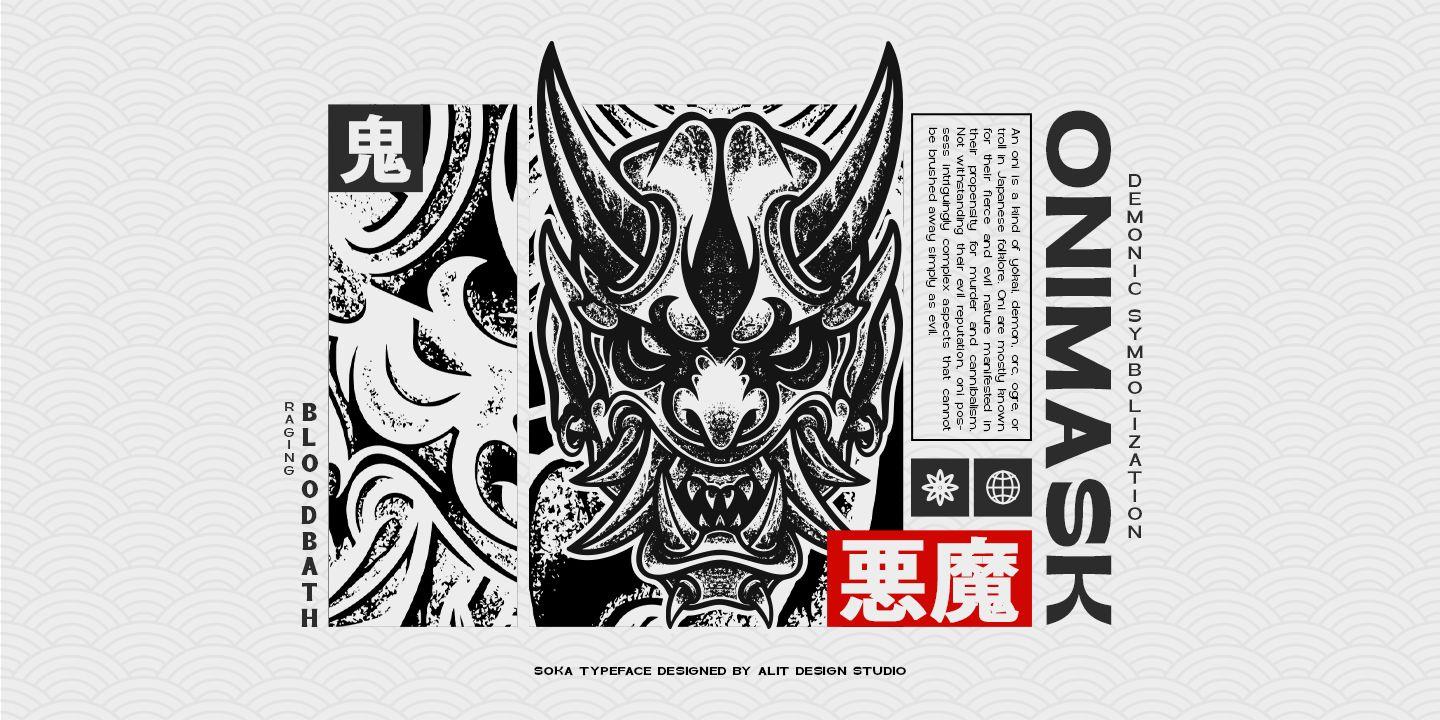
Soka Font
Description de Soka Font
La police Soka s’inspire d’une police sans empattement qui est de style rétro mais toujours moderne et unique. Avec un aperçu avec un concept japonais, la police Soka est unique parmi les autres polices rétro. Les polices Sans Serif telles que la « police Soka » sont très faciles à appliquer à n’importe quel design, en particulier ceux avec un concept élégant et fluide, en plus du fait que cette police est très facile à utiliser aussi bien dans les programmes de conception que dans les autres programmes car tout change et les glyphes sont pris en charge par Unicode (PUA).
La police Soka contient 522 glyphes avec de nombreuses options alternatives uniques et intéressantes. De plus, il existe une famille de polices sans empattement sympa pour le texte d’en-tête et de description, allant de fin à lourd et de fin condensé à fortement condensé. Dans l’aperçu de l’affiche, toutes les lettres sont en police Soka.